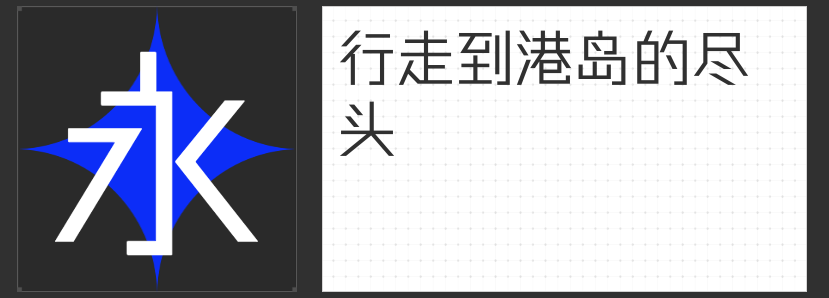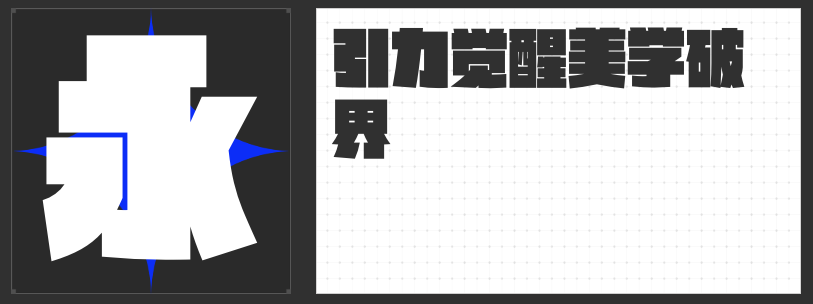
网页设计精选字体推荐:打造专业与美观并存的视觉体验
在网页设计中,字体的选择对于整体视觉效果和用户体验至关重要。今天,为大家推荐四款专为网页设计打造的精选字体,它们不仅具备高度的可读性和专业性,还能为网页增添独特的视觉美感。
第一款推荐的是“励字跨界黑简 超级黑”。这款字体以其超级黑的特性,在网页设计中展现出强烈的视觉冲击力。其线条粗犷、结构紧凑,非常适合用于标题或强调内容,能够迅速吸引用户的注意力。同时,其高度的可读性确保了信息的准确传达,让用户在浏览网页时更加轻松愉悦。
接下来是“造字侠香港硬黑简 常规”。这款直线黑体以其方正简约的设计风格,成为网页设计中的经典之选。其笔画视觉等粗、简洁硬挺,起笔和收笔处做统一斜切处理,使得整体风格更加硬朗统一。西文符号风格硬朗,与中文搭配更加和谐,适用于各类现代简约风格的网页设计。
第三款推荐的是“高手庆科帅黑体 大黑”。这款字体以其硬朗倾斜的整体风格,为网页设计增添了一份动感与活力。其笔画设计简约无过多装饰,横细竖粗,起笔收笔以平切为主,整体倾斜约为6度,使得整体视觉效果更加统一。西文符号以直线为主,加入倾斜的处理,与中文风格相得益彰,适用于各类时尚、动感风格的网页设计。
最后是“字圈也字万能黑体”。这款字体以其独特的喇叭口装饰笔画,成为网页设计中的一大亮点。其字形规矩方正,保留了黑体的基本特征,而每一笔画的端口融入喇叭口装饰,则为其增添了一份端庄而不失活泼的气息。这款字体适用于各类需要展现时代印记或复古风格的网页设计,能够为用户带来独特的视觉体验。
以上四款字体各具特色,适用于不同的网页设计风格和需求。它们不仅能够提升网页的整体视觉效果,还能为用户带来更加舒适、愉悦的阅读体验。希望这些推荐能够帮助你在网页设计中找到心仪的字体,打造出专业与美观并存的视觉作品。